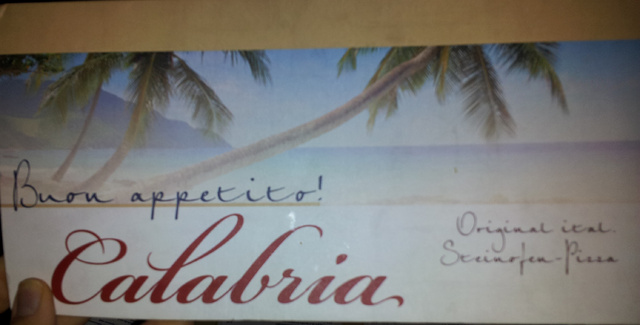
Zwei schriften aus Speisekarte erkennen
ich habe mich gestern bei meinem Italiener in die zwei Schriftarten verliebt, die hier auf dem Deckblatt der Speisekarte zu finden sind. Über jede Hilfe wäre ich sehr sehr dankbar.
Die Bickham allerdings mit Sonderformen.
Wobei ich nicht verstehe, wie man die beiden mischen kann ...
Das geht ganz einfach, man könnte auch noch die Zapfino mit ins Boot holen :shock:
... die Frage ist nur warum, tut man sowas?
Wobei ich nicht verstehe, wie man die beiden mischen kann ...
Weil die beiden am besten zu einem karibischen Palmenstrand passen.
:tuschel:Aber ganz ehrlich: So schlecht finde ich die Kombination in dem Fall gar nicht.